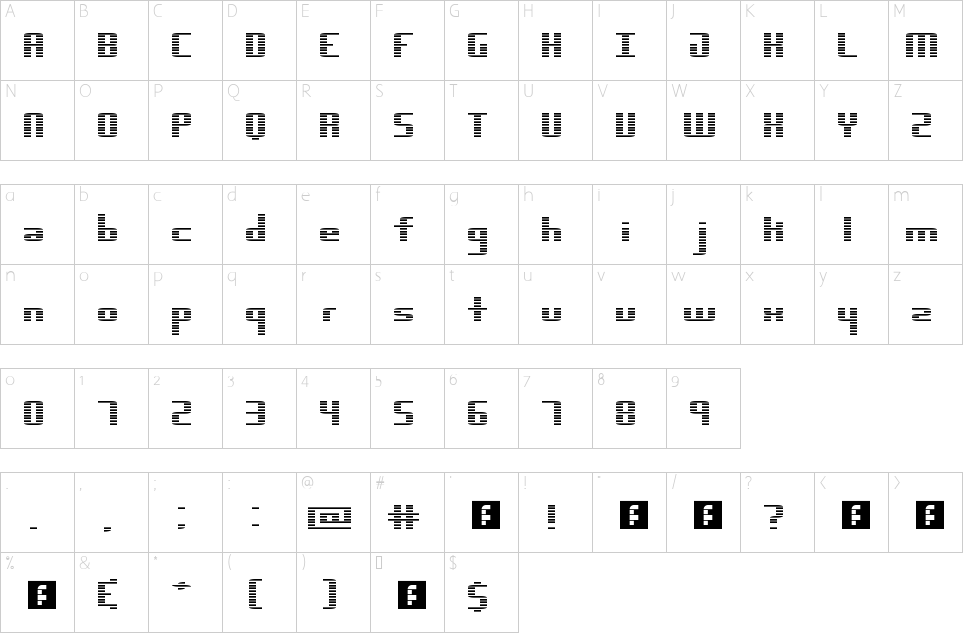
Aqui está uma descrição para a página de download da fonte ‘Dimension Font’, em português do Brasil: O ‘Dimension Font’ é uma elegante e versátil opção entre as muitas fontes disponíveis gratuitamente, especialmente adequada aos profissionais de design. Desenvolvida pelo designer Geronimo Fonts, essa fonte vem pronta para uso tanto no Windows quanto no Mac, permitindo a adaptação perfeita em qualquer ambiente de trabalho digital. A ‘Dimension Font’ é conhecida por sua simplicidade e facilidade de utilização, oferecendo ao design um toque sofisticado sem comprometer o conforto. Seja para criar textos profissionais ou personalizados, essa fonte complementará perfeitamente qualquer projeto criativo. Com seu design meticulosamente cuidadoso e a vasta gama de opções disponíveis, ‘Dimension Font’ é uma excelente escolha tanto para designers digitais iniciantes quanto para aqueles mais experientes que procuram um estilo elegante sem comprometer a personalização. Download gratuitamente agora e deixe-se envolver por seu brilho único.